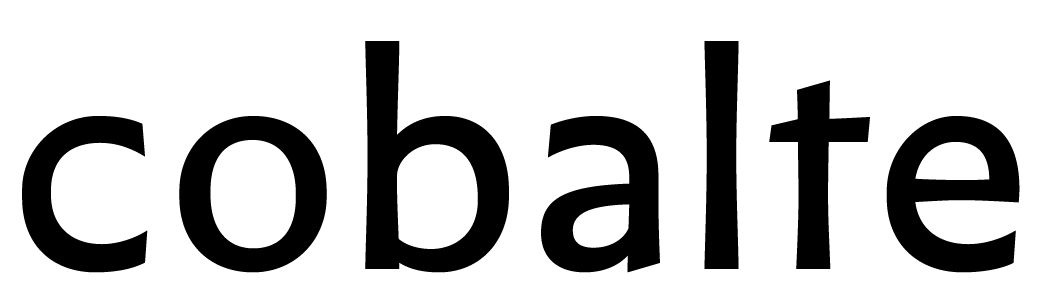
Cobalte
Cobalte는 얼핏 Cogito나 Gemeli의 모던함을 닮아있지만 라인에 미묘한 화려함이 더해진 폰트이다.
산 세리프와 세리프의 경계에 미묘하게 걸쳐 있는 디자인으로 인해 별다른 기법 없이도 밋밋한 본문용 서체 사이에서 포인트를 주는 용도로 활용할 수 있다.